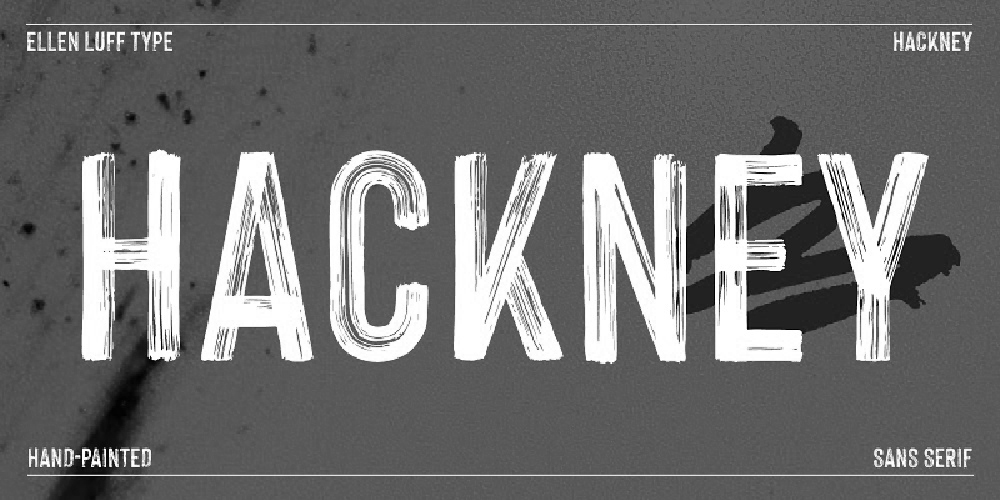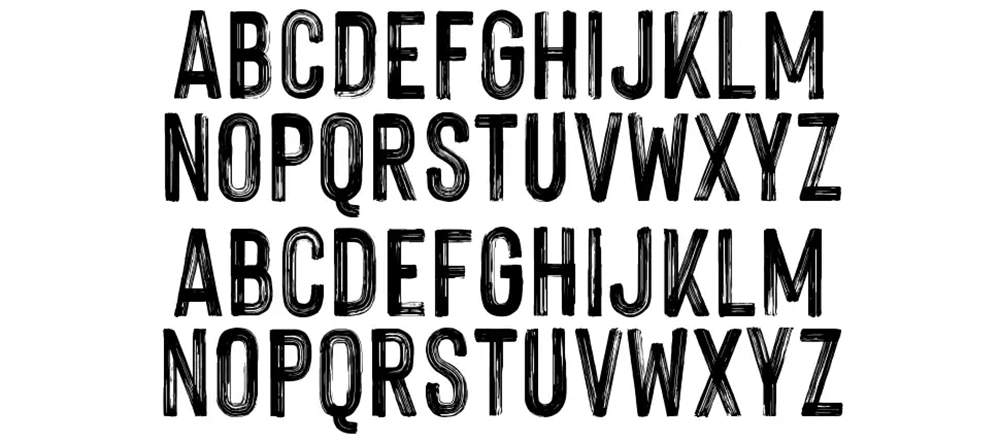
فونت پرمیوم و انگلیسی Hackney Vector Font يک فونت قلمویی قدرتمند با طراحی خاص است که برای پروژهها ايدهآل است. Hackney Vector برای تيترها، پوسترها و موارد ديگر عالی است.
مزایای استفاده از فونت لاتین Hackney Vector چیست؟